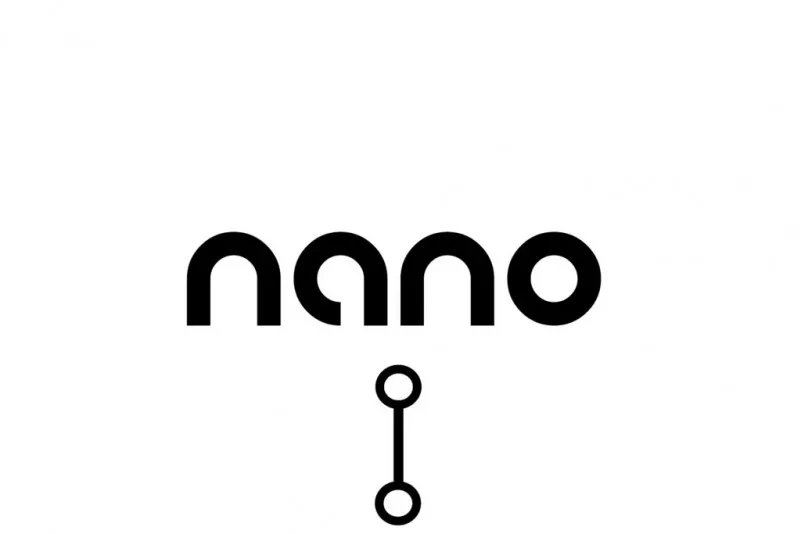
A ‘Nano Font’ é uma elegante seleção de linhas simples que traz uma sensação fresca e geométrica à sua próxima criação visual. Desenvolvida pelo designer Harrison Luke, essa fonte sans serif apresenta um design quase monolinear, conferindo aos caracteres uma simplicidade clássica e durabilidade. Essa característica geométrica é temperada por bordas levemente suaves e formas vivas que garantem uma aparição moderna e vibrante. Com linhas ultra-modernas e minimalistas, esta font se destina perfeitamente para o uso em marcas modernas e logos, tornando-a um recurso vital para designers procurando criar identidades visuais atemporais e modernas.